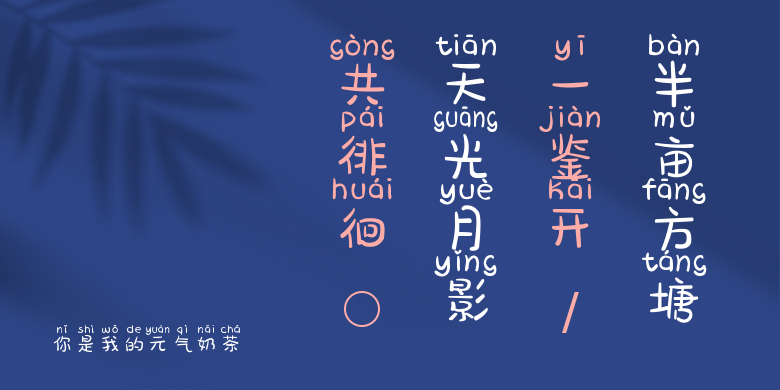
你是我的元气奶茶
你是我的元气奶茶,这款字体结构工整、笔画清晰,兼顾美观与易读性,适用于标题、正文、海报、包装、LOGO 等多种场景。字形优雅稳定,风格百搭耐看,适配日常排版与创意设计,让文字呈现更舒适、更具质感。你是我的元气奶茶一笔一画,皆是细节,以均衡的比例、流畅的线条打造舒适视觉体验,字形端正大气,风格简约现代。无论是商业设计、品牌宣传还是日常排版,都能轻松驾驭,让文字更有格调与力量。你是我的元气奶茶字体下载。